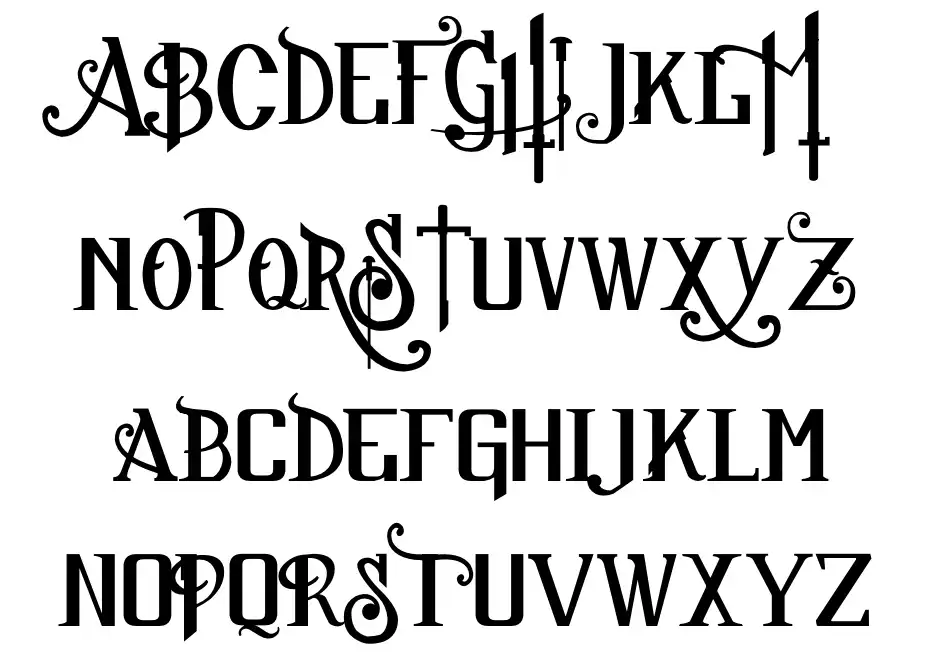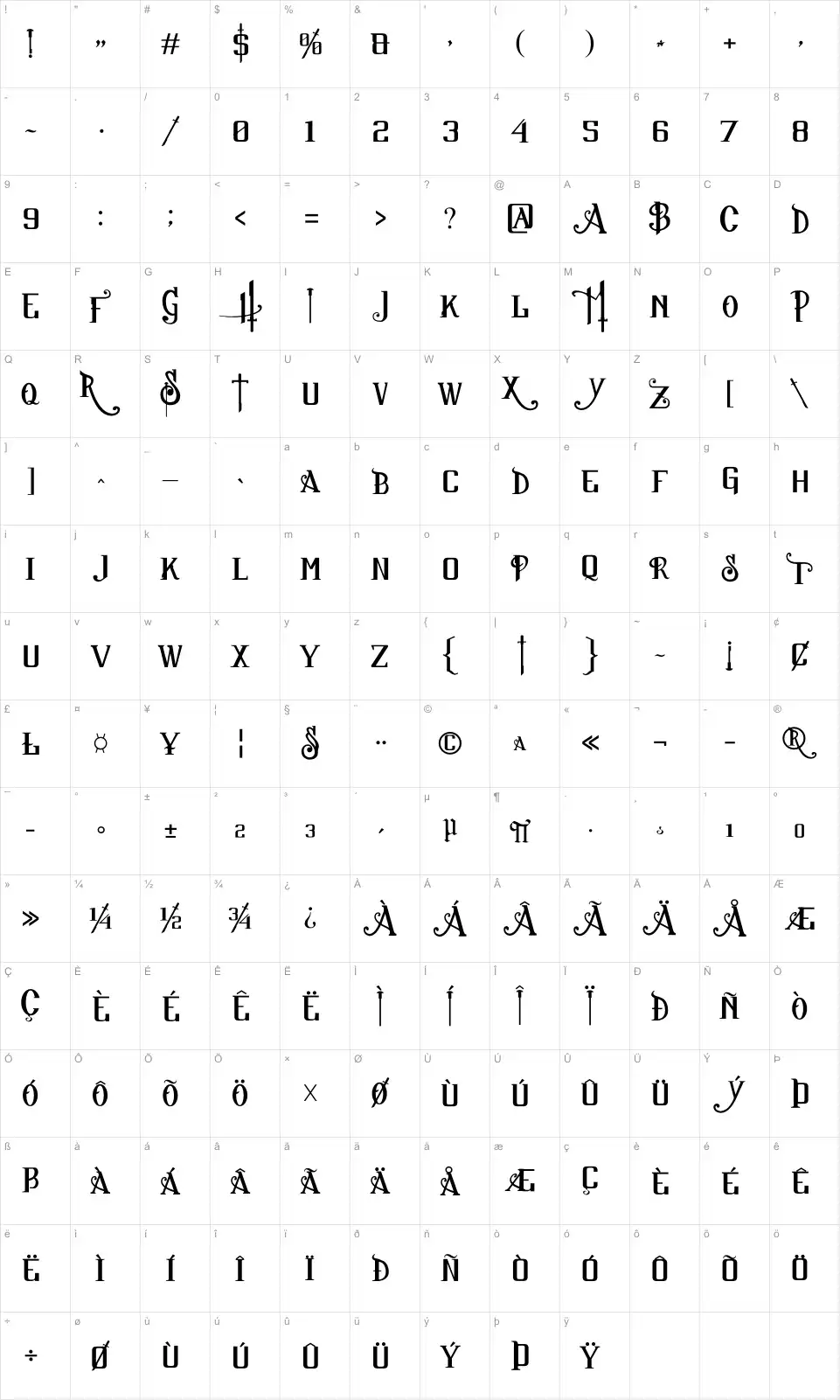
Sucker Font – Download Grátis
A fonte Sucker Font, criada pelo designer Juan Casco, está disponível para download e teste gratuito para uso pessoal. Esta fonte pertence à categoria Fancy, entre as várias opções disponíveis. Com licença para uso pessoal, o Sucker Font pode ser baixado no formato TTF e é uma excelente escolha para aqueles que buscam algo despojado e peculiar em seus projetos. Adicionada à nossa base de recursos em 12 de julho de 2022, a Sucker Font já recebeu 2451 downloads, o que prova sua popularidade entre os criativos. Se você está procurando uma fonte divertida e única, o Sucker Font é uma ótima opção para adicionar um toque especial a suas criações. Visite o site do designer, https://www.juancasco.net, para explorar mais recursos e novidades.
Designer: Juan Casco